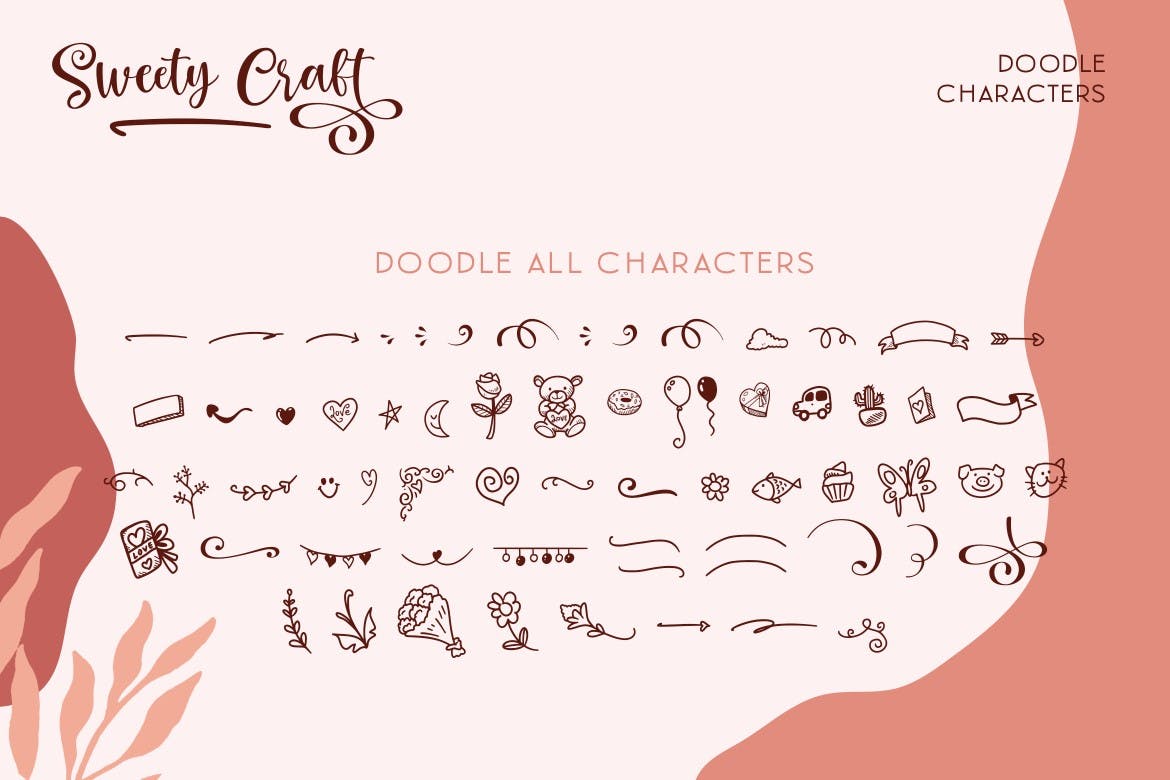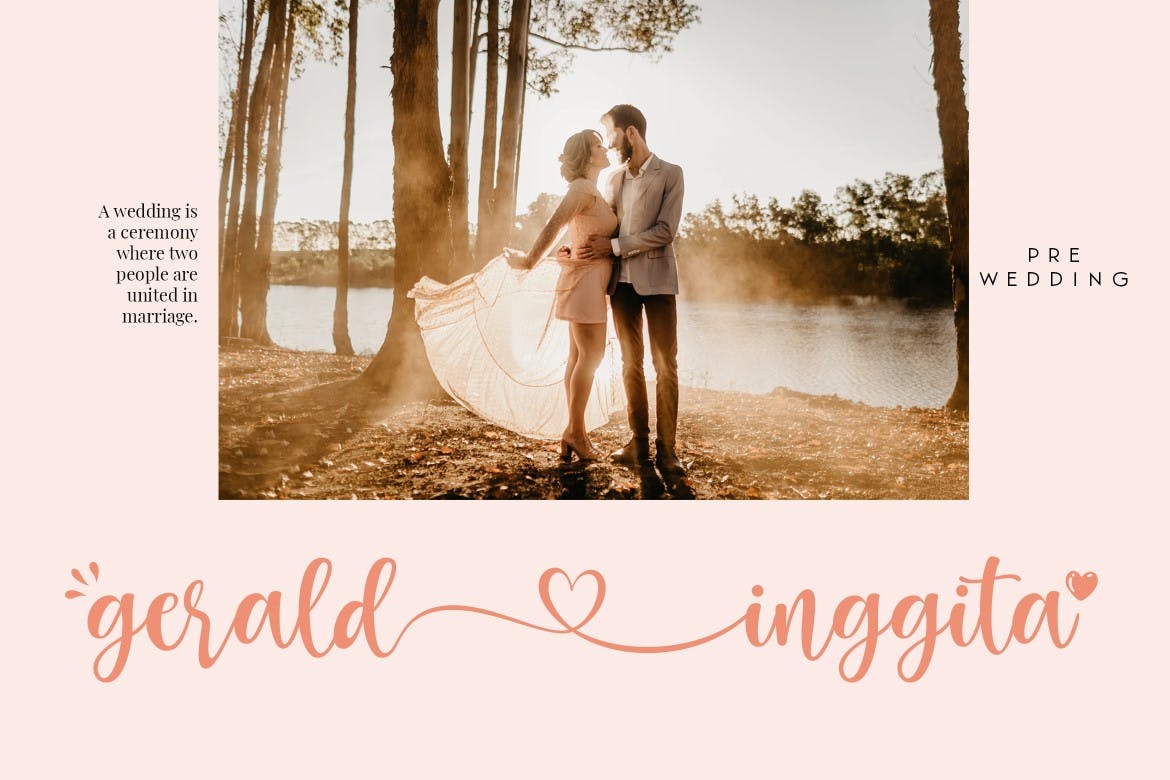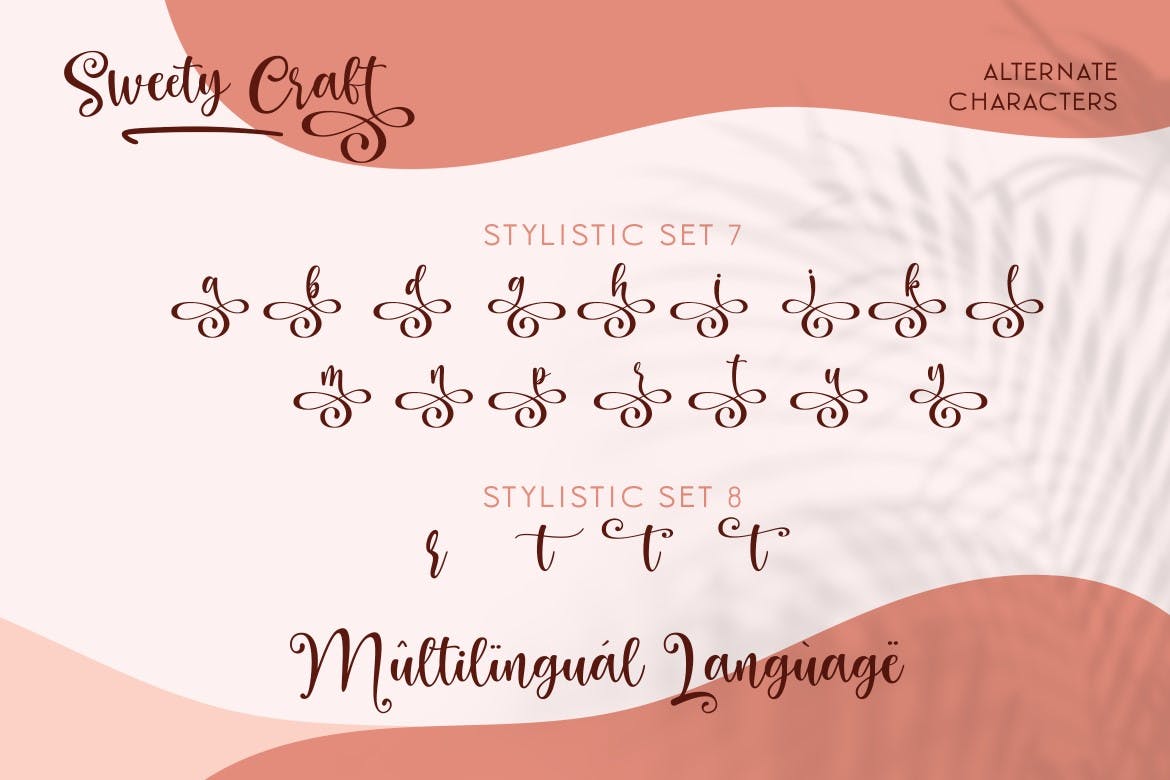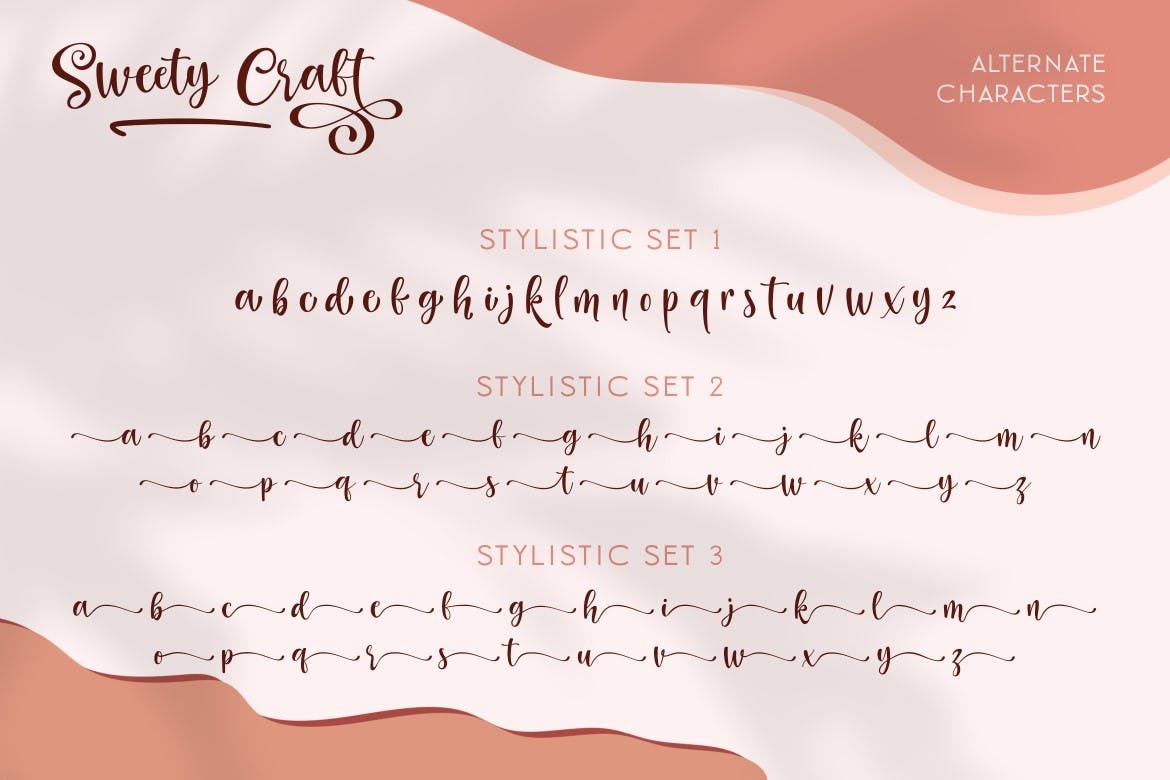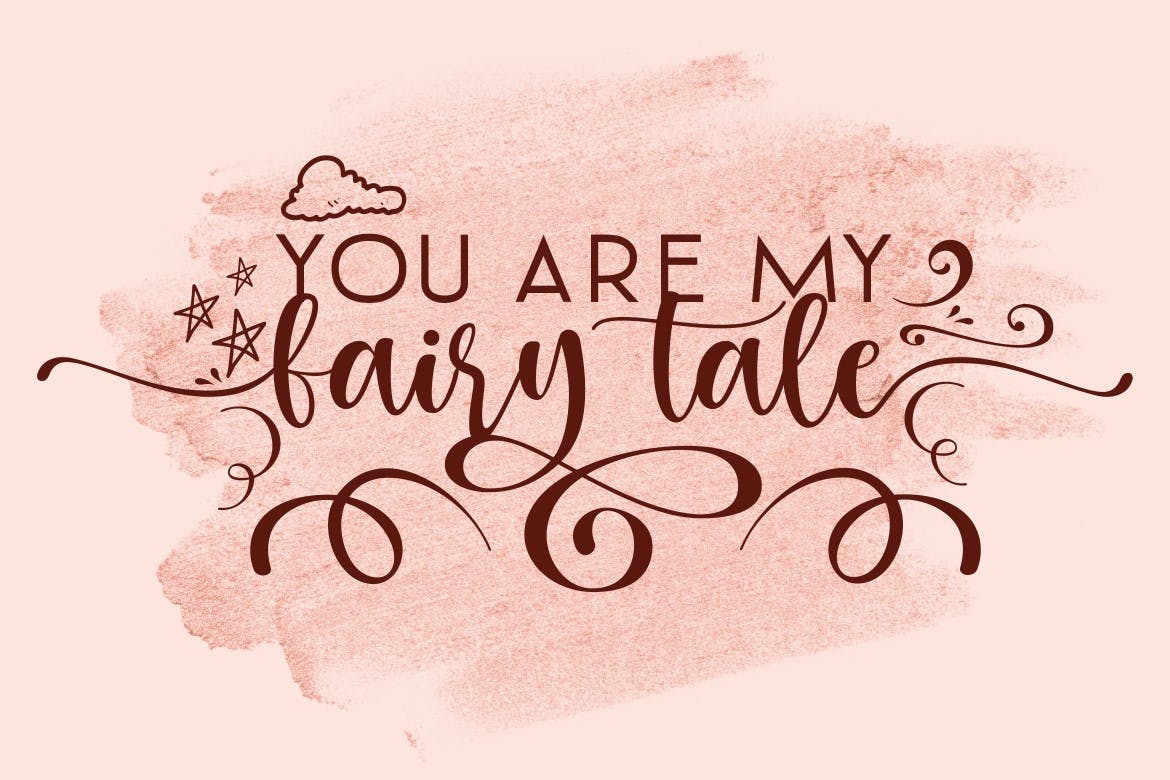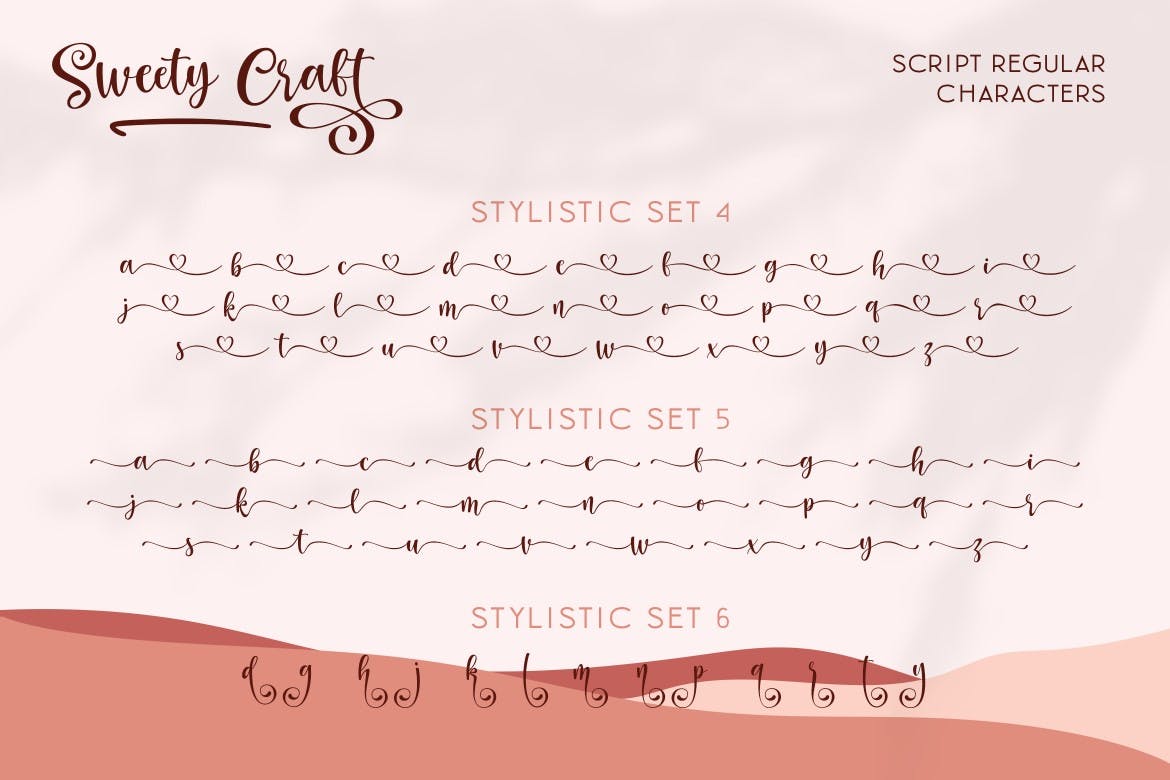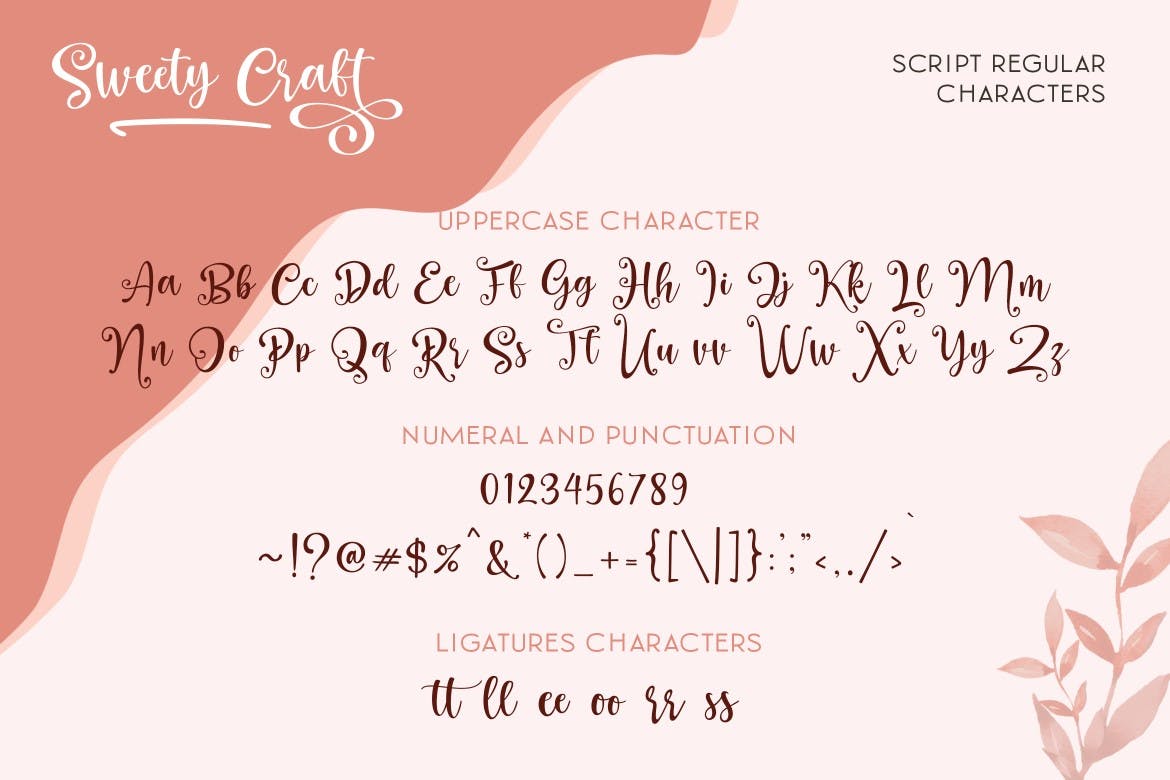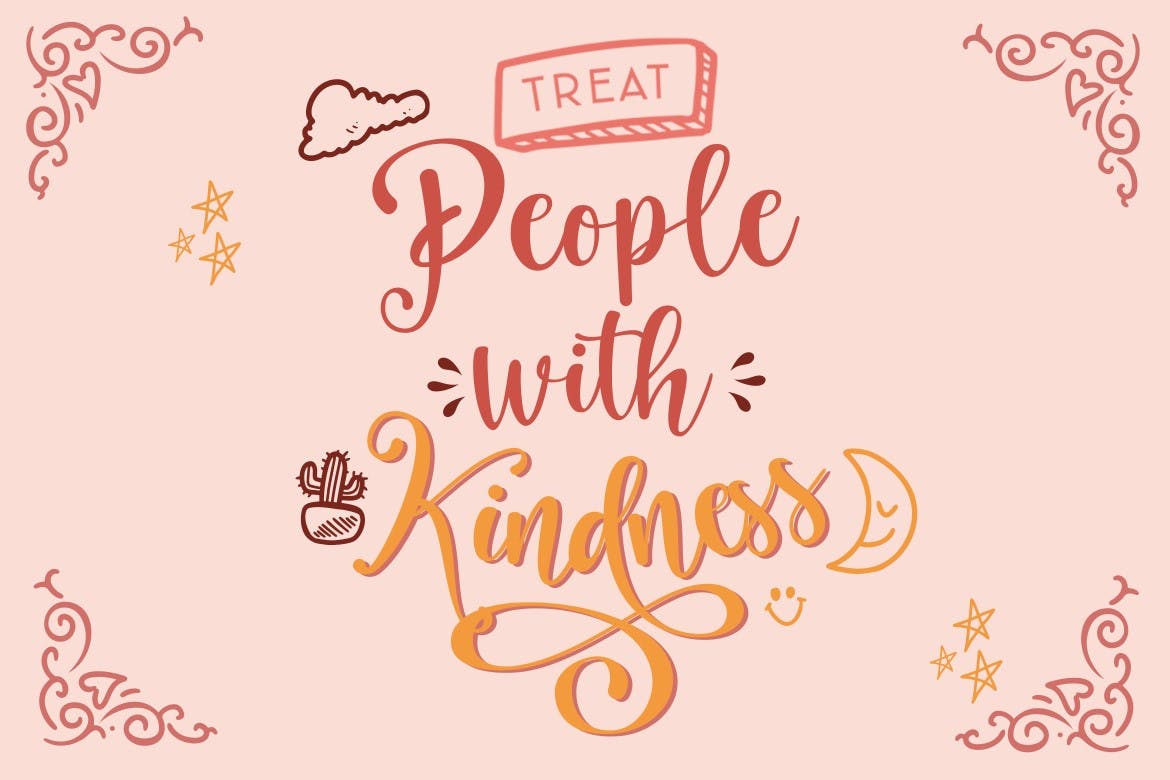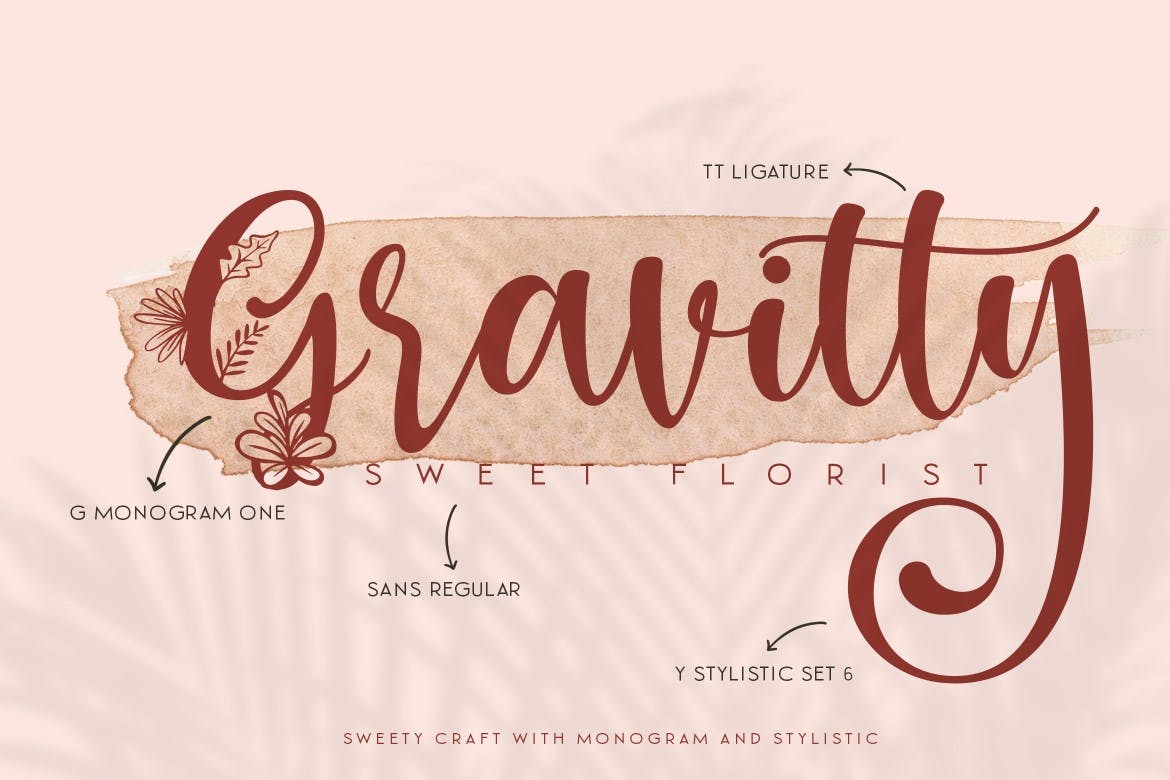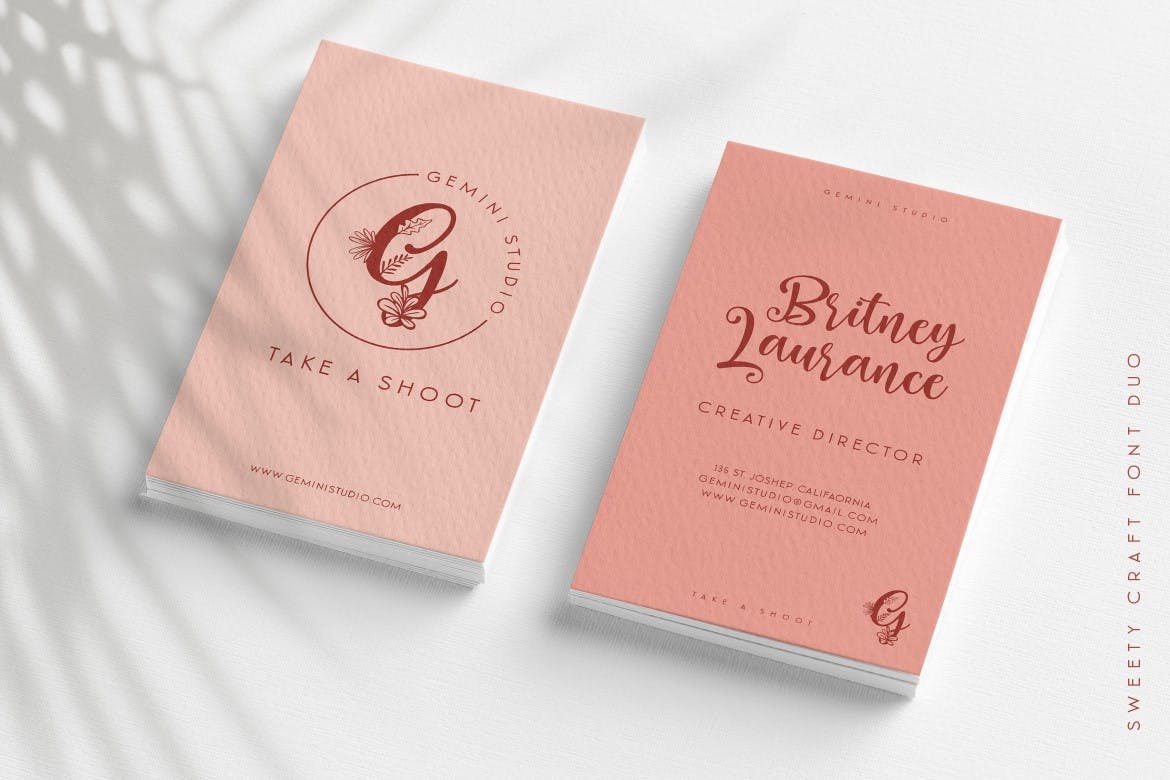
دانلود فونت Sweety Craft برای طراحی‌های زیبا
Sweety Craft Business Crafting Font
فونت Sweety Craft مناسب برای طراحانی که به دنبال خلق پروژه‌های زیبا هستند.
فونت Sweety Craft طراحی شده برای طراحانی است که عاشق ساخت پروژه‌های زیبا مانند صنایع دستی، SVG، لباس، پوستر، مد، لوگو و بسیاری دیگر هستند. این فونت در واقع یک فونت دوگانه است، اما با گزینه‌های متعددی که دارد، به شما این امکان را می‌دهد که طراحی‌های ترکیبی خوبی ایجاد کنید. همچنین، شما با خرید این فونت، چندین بونوس دریافت می‌کنید که شامل ۳ فونت مونوگرام و ۵۲ دودی است.